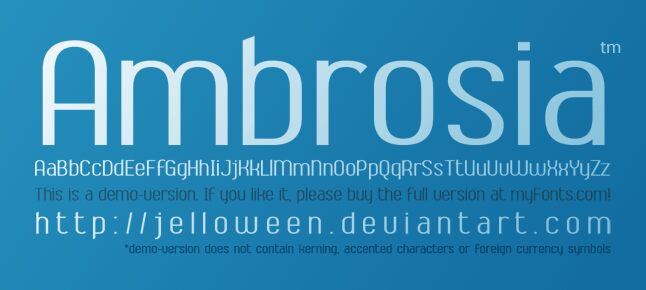
Ambrosia von Tjarda Koster ist eine serifenlose Schrift, die einfache Buchstabenformen in etwas dezent Besonderes verwandelt. Ihre hohen, schlanken Proportionen werden durch großzügig abgerundete Ecken und offene, pillenförmige Punzen abgemildert, wodurch sie sauber und doch ein wenig genussvoll wirkt – wie glänzende Tinte auf glattem Papier. Die gleichmäßige Strichstärke und saubere Abstände sorgen für eine klare, moderne Anmutung, während die feinen Kurven eine warme, menschliche Note verleihen.
Mit Ambrosia erhalten Sie eine serifenlose Schrift, die sowohl elegant als auch zugänglich für Branding, Verpackungsdesign, redaktionelle Titel, Hero-Texte, Plakate und Logos ist. Diese kostenlose Schrift glänzt besonders in größeren Schriftgraden, wo die abgerundeten Formen wirken können, und lässt sich hervorragend mit einer neutralen Grotesk oder einer leichten geometrischen Sans für den Fließtext kombinieren.